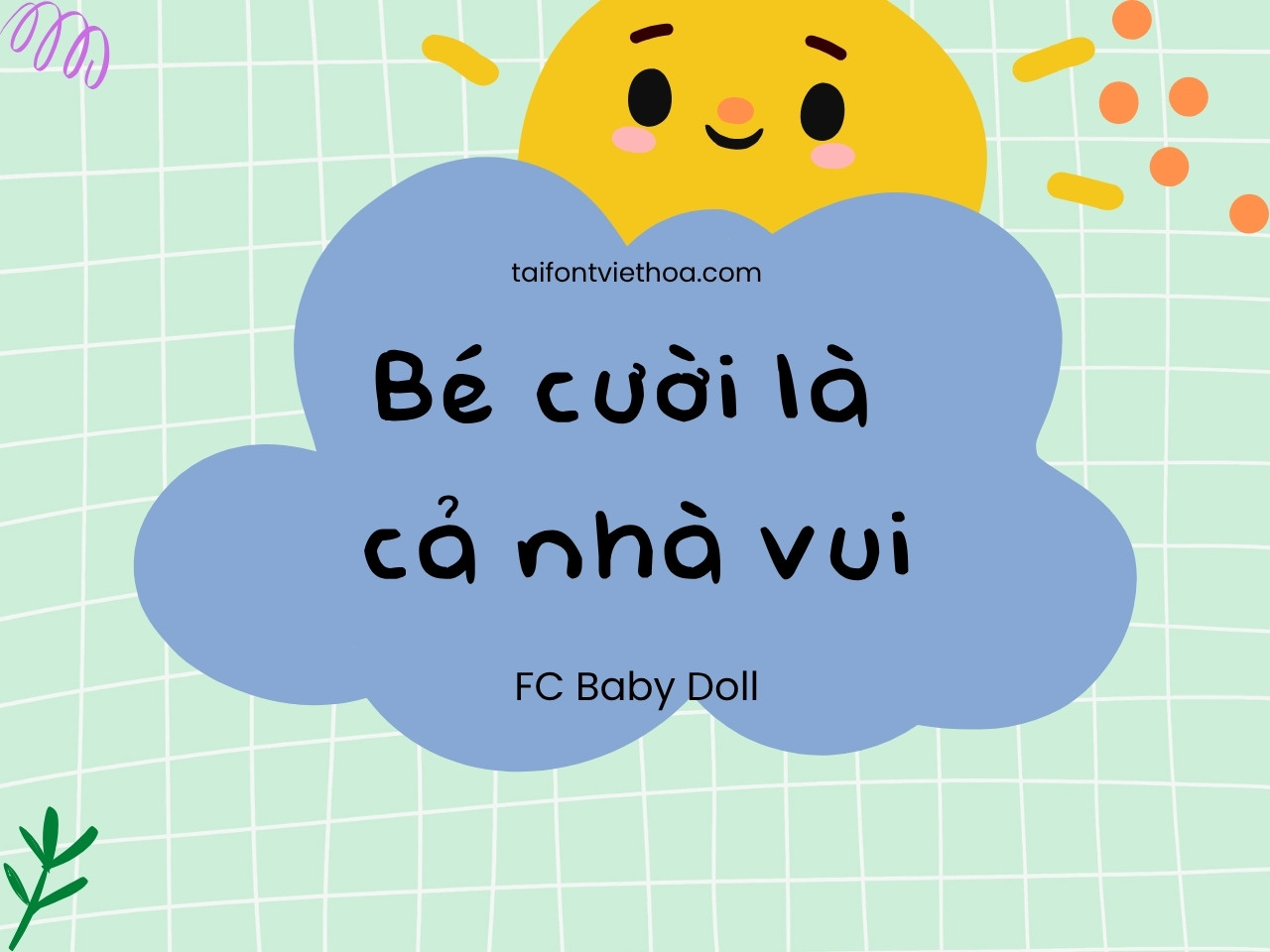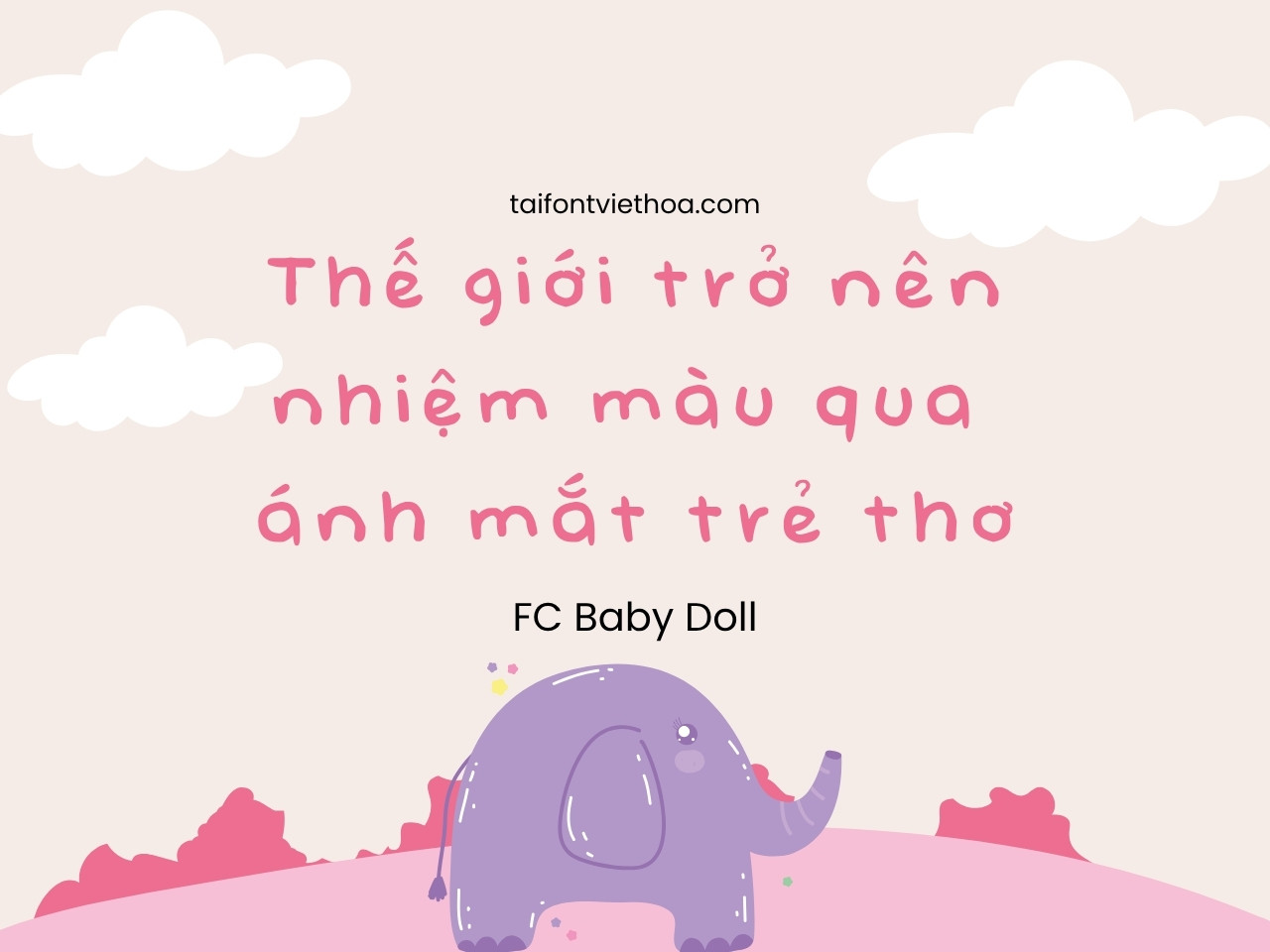
Giới thiệu về font Baby Doll và phiên bản Việt hóa
FC Baby Doll là phiên bản Việt hóa từ font gốc “Baby Doll” – một thiết kế viết tay mềm mại và đầy cảm xúc của Denise Bentulan. Với phong cách handwritten tự nhiên, hơi phá cách nhưng vẫn dễ đọc, font nhanh chóng được yêu thích trên các nền tảng như Dafont và Fontspace, đặc biệt trong các dự án mang hơi hướng thủ công, sáng tạo cá nhân hoặc truyền tải cảm xúc nhẹ nhàng.
Khác với phiên bản “1FTV VIP Baby Doll” đã từng được giới thiệu trước đó, phiên bản FC Baby Doll là một bản Việt hóa hoàn toàn riêng biệt, được thực hiện và tối ưu bởi cộng đồng Font Chuẩn, đảm bảo đầy đủ dấu tiếng Việt, khả năng tương thích tốt với bộ gõ và giữ nguyên tinh thần bay bổng, thân thiện của bản gốc. Các ký tự có dấu được tinh chỉnh tỉ mỉ để đạt hiệu quả thị giác nhất quán, phù hợp với nhu cầu sử dụng trong thiết kế hiện đại hoặc phong cách cổ điển.
Đặc điểm thiết kế và ứng dụng thực tế
FC Baby Doll mang đậm chất viết tay ngẫu hứng với các nét cong mềm, độ nghiêng nhẹ và các ký tự không đồng nhất hoàn toàn về chiều cao – tạo nên cảm giác chân thực và gần gũi như chữ viết tay thật. Font không quá cầu kỳ về chi tiết nhưng lại rất thu hút nhờ phong cách phóng khoáng, mang nét nữ tính nhẹ nhàng nhưng không kém phần cá tính. Sự không hoàn hảo có chủ đích giúp Baby Doll dễ dàng truyền cảm hứng cho các thiết kế sáng tạo.
Font này đặc biệt phù hợp cho các thiết kế thiệp mời, bao bì sản phẩm thủ công, các bài post mạng xã hội, thương hiệu cá nhân, thiết kế thời trang, nhật ký sáng tạo hoặc những ấn phẩm cần cảm giác tự nhiên và biểu cảm. Ngoài ra, đây cũng là lựa chọn hoàn hảo cho các dự án quảng cáo mang tính cá nhân hóa hoặc nhấn mạnh chất nghệ thuật, sáng tạo tự do.